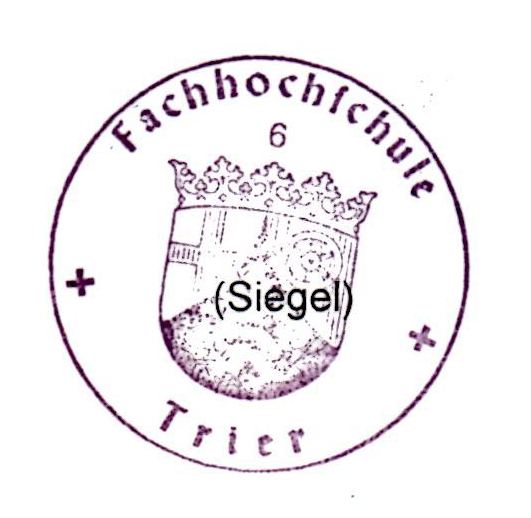
Fachhochschule Trier Wappen Schrift
Ich bin aktuell auf der Suche nach alten deutschen Schriftarten
Habe das logo der Hochschule Trier entdeckt
Kann mir jemand sagen welche Schriftart das ist?
Wie Phoibos schon sagt: es muss nicht zwingend perfekt zu einer Druckschrift passen. Es sieht aber zumindest gesetzt aus. Für eine gezeichnete Vorlage wären die Profis früher anders mit ch/ſch umgegangen.
Ziemlich gut passen könnte eine schmale Wallau:
Die hat auch diese einfache, antiqua-artigen Großbuchstaben.